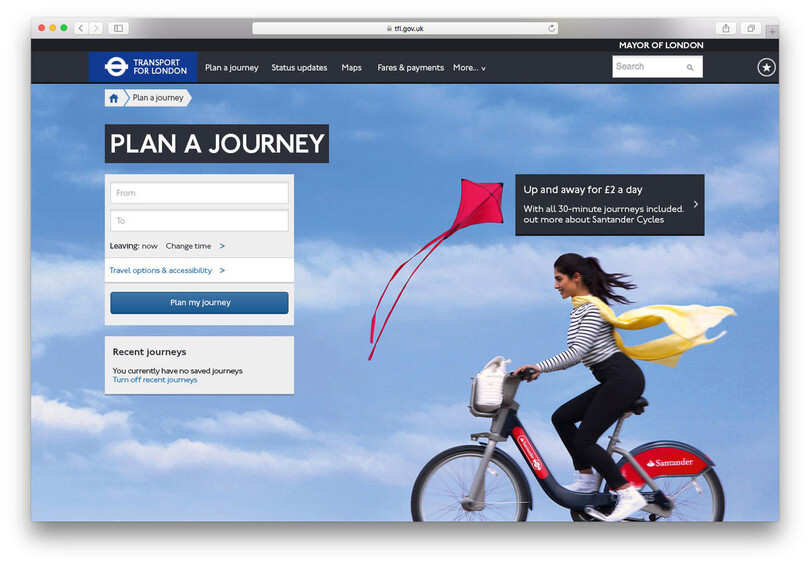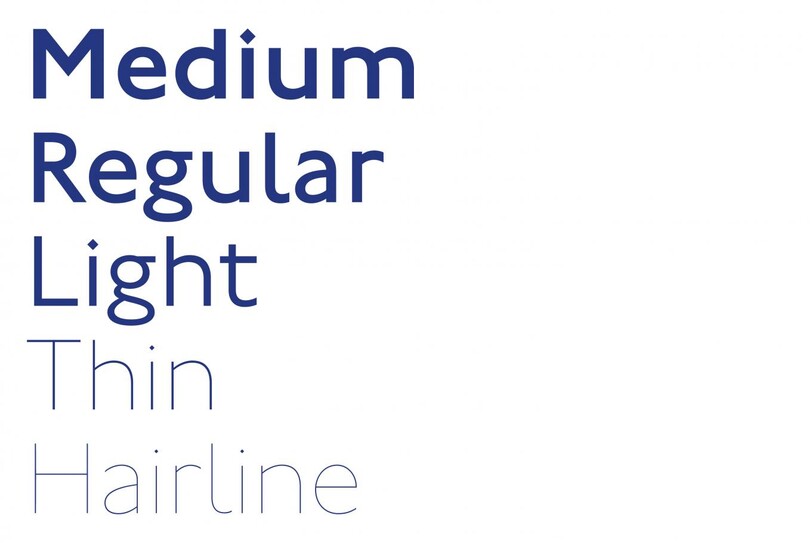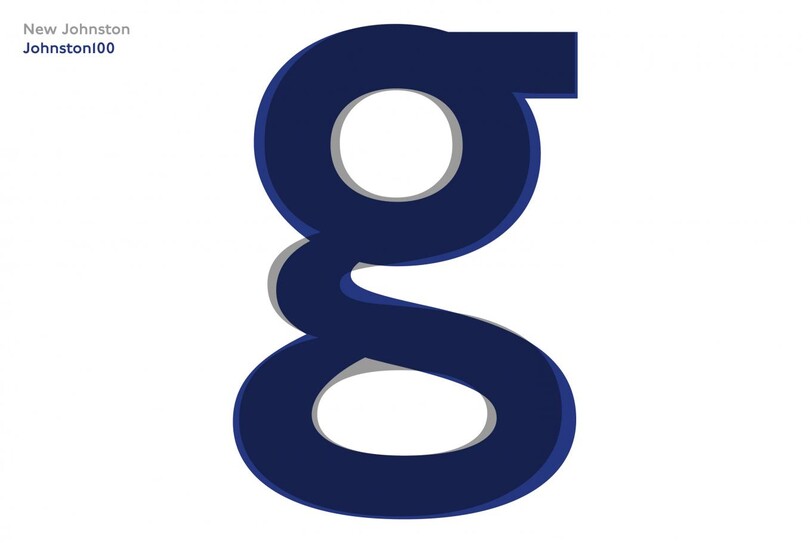
100年前のロンドンの「味」を受け継いだ書体、Johnston100をリリース
Monotypeは、ロンドン交通局より100年の歴史を誇る書体Johnstonの刷新を依頼されました。
Johnston書体は、100年にわたり、ロンドンの交通機関における路線図や案内表示板の文字として親しまれてきました。
オリジナル版は1913年に作成されました。英国人のアーティストでカリグラファーでもあったEdward Johnstonは、ロンドンの伝統にしっかりと根付きながら20世紀に属する「大胆なシンプルさ」を持つ文字の制作という任務を負うことになりました。完成されたそのデザインは、ペン先のひし形を活用した7種類の線をプロポーションのベースにし、ウエイトはわずか1種類。特徴的なひし形は、「i」と「j」の文字に含まれる小さな黒い点に見ることができます。
特徴的な「i」と「j」のひし形の点
オリジナルにあたる書体Johnstonのデザインは1916年に発表されました。以来Johnstonは100年にわたり使われてきました。直近の更新は1970年代後期、Banks & Miles社の河野英一氏が当時新しかった植字技術用にリデザインを行った時のことです。
細かい改訂はありましたが、Johnstonはロンドンを象徴する書体、また視覚的アイデンティティとして君臨し、観光客や市民に親しまれてきました。
Johnstonがロンドンの視覚的アイデンティティの確立に果たした功績は、英国のDitchling Museum of Art + Craftで開催されたロンドン地下鉄100周年記念展覧会で改めて評価され、書体の世界における古典傑作としての揺るぎない地位を確立する運びとなりました。
移り変わる時代における新たな需要によって生まれたJohnston100ファミリー
Johnstonは1世紀にわたってロンドン交通局の視覚的アイデンティティであり続けてきました。しかし、ロンドンの交通システムの拡大に従い、路線図からモバイルアプリに至るまで、情報伝達に使用される媒体が急速に拡大したため、ロンドン交通局 (TfL) は、モバイルなどの小さい文字として表示される場合でもオリジナル版でのデザイナーの意図を損なうことなく、Johnstonの機能を拡張、更新する必要に迫られたのです。
Johnston100は、路線図からモバイルアプリに至るまで、ロンドンの交通機関の拡大に対処するという目的のもとに依頼、制作されました。
「Monotypeにお願いしたのは、Johnstonの原則に立ち返り、現在のフォントの在り方を省みながら、過去100年の旅で失ったものを確認するということでした(ロンドン交通局のデザイン主任Jon Hunter氏)」
「Johnstonをリデザインし直すこと自体には積極的ではなかったものの、様々な理由で物事が変化してきたことも実感していました。たとえば、改訂に伴って一部の小文字のデザインは当初のユニークさを失っていました。」
新しいJohnston100ファミリーには、今回新たに開発されたHairlineとThinを含むウエイトが5種類含まれています。この2つの新しいウエイトは、オリジナルの書体の最大の特徴であった書体の質量を全てそぎ取り、シンプルな骨格だけにするというチャレンジに成功しています。これらは、精巧なデザインとリサーチの賜物と言えるでしょう。新ファミリーであるHairlineに見られるように、文字のユニークな特徴を失うことなくコンテンポラリーな仕上がりを実現するに至りました。
新しいJohnston100ファミリーには、今回新たに開発されたHairlineとThinを含む5種類のウエイトがあります。
書体が持っていた「味」を取り戻す作業
また、これまで書体の確立してきたアイデンティティを維持するために、Monotypeの書体ディレクター、Nadine Chahineとシニア書体デザイナー、Malou Verlommeは、100年前のアーカイブに保管されている開発された当初のスケッチを徹底的に研究し、書体のルーツを辿りました。結果、2人は、小文字の「g」の斜めに湾曲した部分や、幅を広めに取った大文字の「U」など、Johnstonが進化の過程で失った要素を再び復元して反映するに至りました。
Johnston100は、小文字の「g」の斜めに湾曲した部分など、Edward Johnstonによるオリジナルデザインの特徴や味を復活させました。
「Johnstonの最新のバージョンはどこか少し機械的で、均一とも言える雰囲気になってきていました。元の書体にあった特徴は、癖があって少し奇抜に思えましたが、良い味わいがありました。それらを再び復刻できたら、書体の持っていた元来の精神を取り戻せるかもしれないと思ったのです(Chahine)」
デザイナーたちは初期のロンドン地下鉄のポスターも参考にしましたが、地下鉄に乗る喜びを表現しているデザインがたくさんありました。現在のコミュニケーションではあまり取り上げられない要素です。ChahineとVerlommeは、少し幅を広げた書体デザインを復活させることで、書体自身に加え、地下鉄に乗るという体験においても、広々とした感覚を再び取り入れることに成功しました。
「つまり、機械的で完璧に仕上げることではなく、ちょっと凝った、小さなディテールをすべて味として受け入れることが大切だったのです(Chahine)」
手を取り合って歩いてくれる仲間のような書体
Johnston100は、2016年7月に導入されました。最初は地下鉄路線図やポスターなどの印刷物を中心に徐々に展開し、2018年にロンドンで開通予定のクロスレール「エリザベスライン」を含む、ロンドン交通局の列車や駅の看板などにも使用される予定です。
「ブランディングとJohnston100は、ロンドン地下鉄の目に見えないスタッフの一員なのです(Hunter)」
「一緒に手を取り合って歩いているような存在です。それも大変素晴らしいところです。ブランディングと書体のセットというものが、とてもユニークな存在だからです(Chahine)」